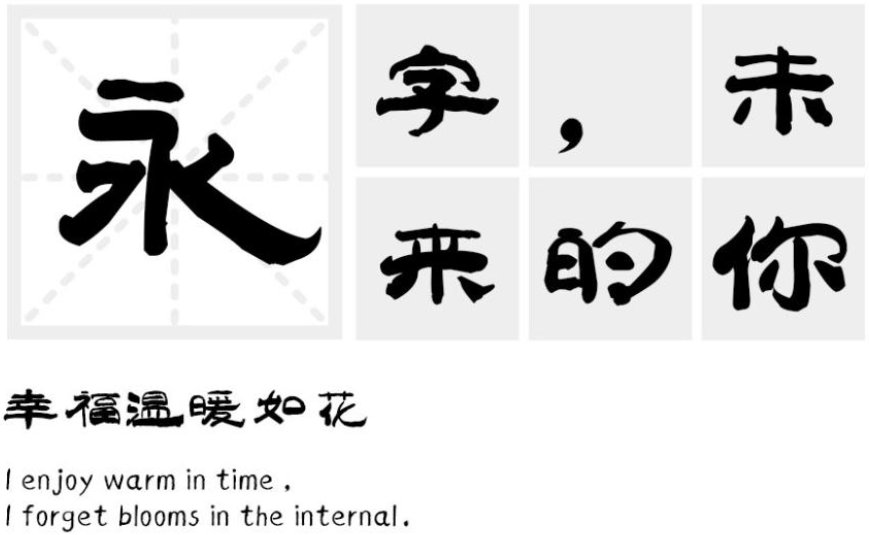
汉标太极体是汉标字库推出的一款有趣且个性鲜明的中文简体字体,作者在创作时力求太极元素,端庄平稳,中正安舒,字体易于识别、字型规范而不失特色。行书的运笔加入了一些抑扬顿挫及个别笔画的大舒展,形似人在打太极的感觉。(点击字体名字可直接免费下载)
字体名称:汉标太极体
字体类别: 书法类字体
适用场景:广告、海报、影视
字形展示: